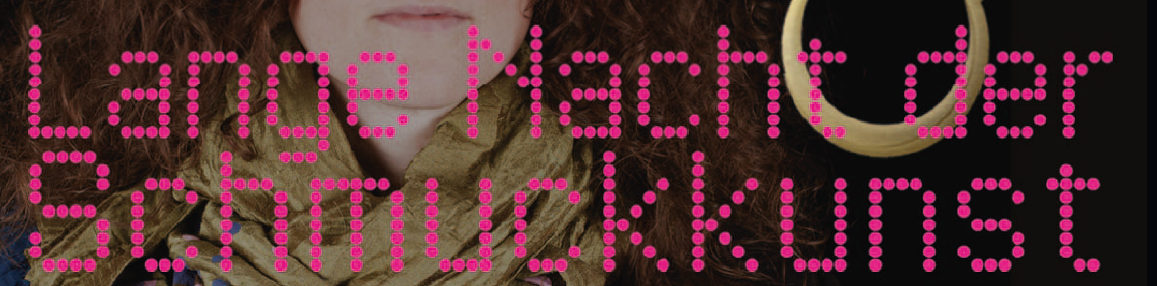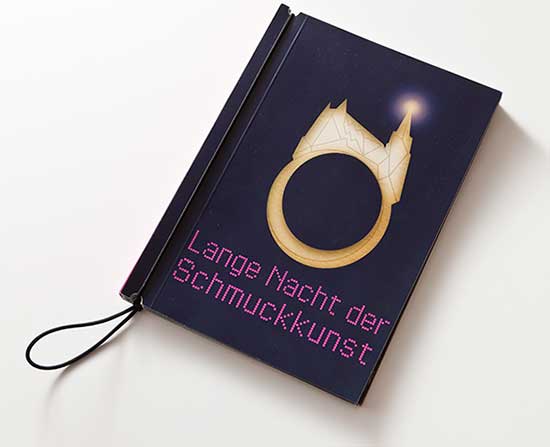
Schriftart aus kleinen Kreisen gestaltet gesucht
Die von mir gesuchte Schrift besteht aus lauter kleinen Kreisen, siehe Bild attached. Wie heisst sie?
Ein klein wenig größer (hab aber auch keine Ahnung …)
Wenn es nicht genau die sein muss, dann würde ich die Perform wärmstens empfehlen – die hat trotz der Reduktion auf Pünktchen sehr sehr schöne Formen. :-)
Ein klein wenig größer (hab aber auch keine Ahnung …)
Das ist eine Dot-Matrix-Schrift. Das Stichwort lautet Dot. Es gibt eine recht ähnliche Schrift BPDots.
Leider hat die 7x5 statt der 9x5 wie in den von Dir gezeigten Beispiel. Höhe 9 Dots -> 9Pin. Tipps für die weitere Suche sind die Stichworte/Kategorien: Dot-Matrix, LCD, LED, Pixel, Bitmap ...
Oder du erstellst ihn dir mit fonstruct schnell selbst ;-)